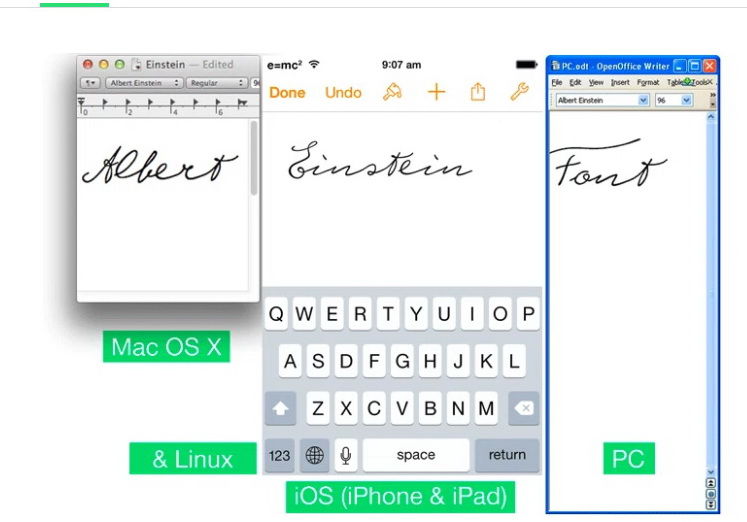
Дизайнер создаёт шрифт на основе письма Альберта Эйнштейна
Дизайнер Гаральд Хейзер из Франкфурта работает над шрифтом, имитирующим письмо Альберта Эйнштейна.
Для создания шрифта дизайнер изучил большое количество рукописей учёного. В данный момент уже существует работающий прототип шрифта. Деньги создателю требуются для продолжения работы над шрифтом.
По заявлению Хейзера, главная сложность заключается в том, что при письме от руки соседние буквы никогда не получаются одинаковыми, и потому необходимо вкладывать сразу несколько вариантов написания, которые будут комбинироваться при печати. Ранее Хейзер уже создал по той же методике гарнитуру на основе рукописей Зигмунда Фрейда.